8 Font Feminin di Canva yang Bikin Desainmu makin Anggun dan GirlyÂ
- Memilih font dalam desain grafis adalah langkah krusial untuk menciptakan kesan dan nuansa yang diinginkan.
- Font feminin sering digunakan untuk undangan pernikahan, branding produk kecantikan, dan produk cewek lainnya.
- Canva memiliki berbagai pilihan font feminin yang bisa disesuaikan dengan gaya desain sendiri. Pilihlah sesuai dengan fungsi desainmu.
Dalam dunia desain grafis, memilih font merupakan langkah krusial buat menciptakan kesan dan nuansa yang dihasilkan. Font yang tepat bisa membantu kamu buat menyampaikan pesan kepada target audience dengan lebih efektif. Buat kamu yang ingin menambahkan sentuhan feminin dan anggun pada karya desainmu, Canva memiliki berbagai pilihan font yang bisa kamu kreasikan sesuai gayamu sendiri.
Menggunakan font feminin bisa memberikan sentuhan lembut dan girly pada desain grafis. Itulah mengapa font dengan tema ini biasanya sering digunakan buat undangan pernikahan, branding produk kecantikan, dan produk-produk cewek lainnya. Kalau kamu lagi mencari font feminin buat melengkapi desainmu yang girly abis, intip delapan rekomendasi font di Canva yang bisa kamu coba terapkan ini, yuk!
1. Twister, font dengan bentuk goresan terkesan santai, cocok buat desain produk cewek yang ingin menonjolkan sisi kreatif dan ceria
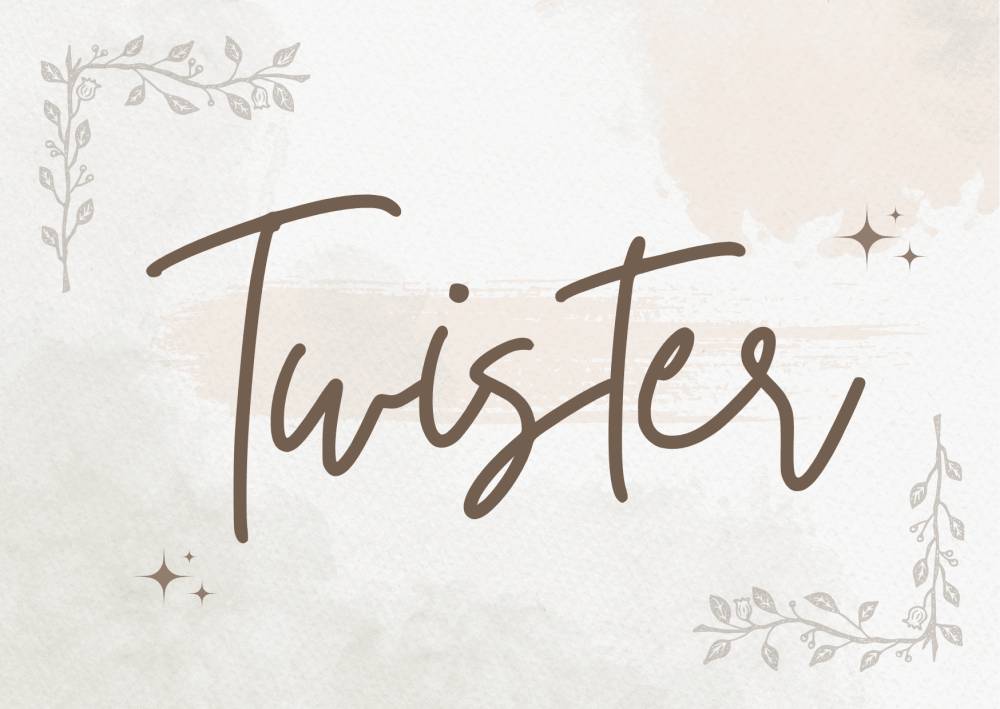
ilustrasi font Canva (dok. pribadi) 2. Angella White, font script dengan goresan halus dan lembut yang pas menambah sentuhan elegan branding produk kecantikan
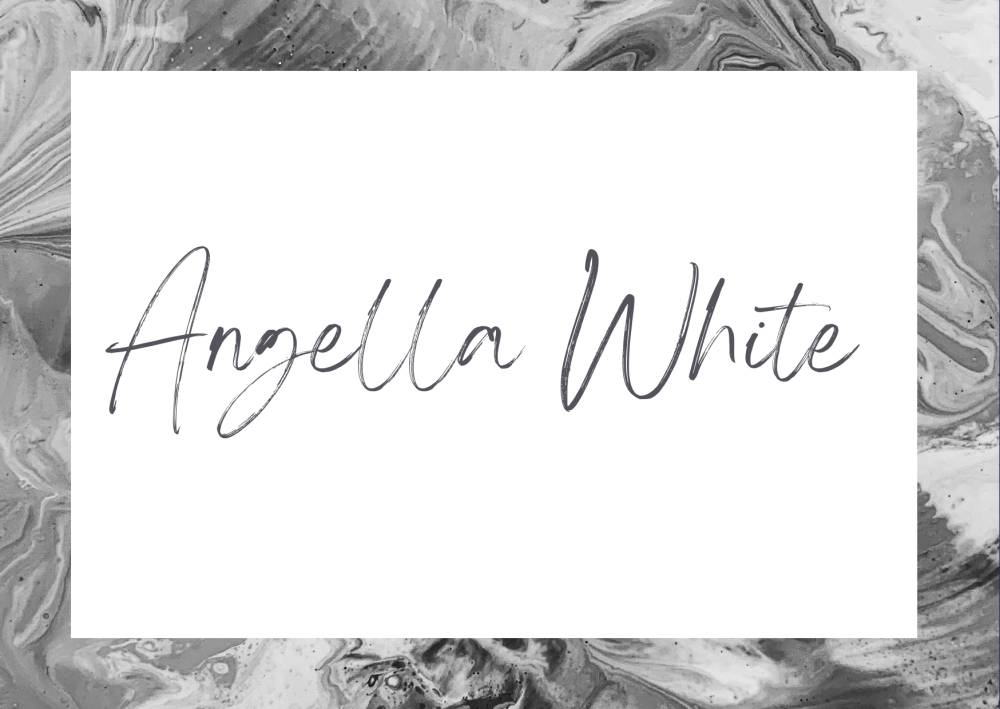
ilustrasi font Canva (dok. pribadi) 3. Virtual, font script yang terkesan clean, cocok digunakan buat desain produk cewek dengan tema minimalis
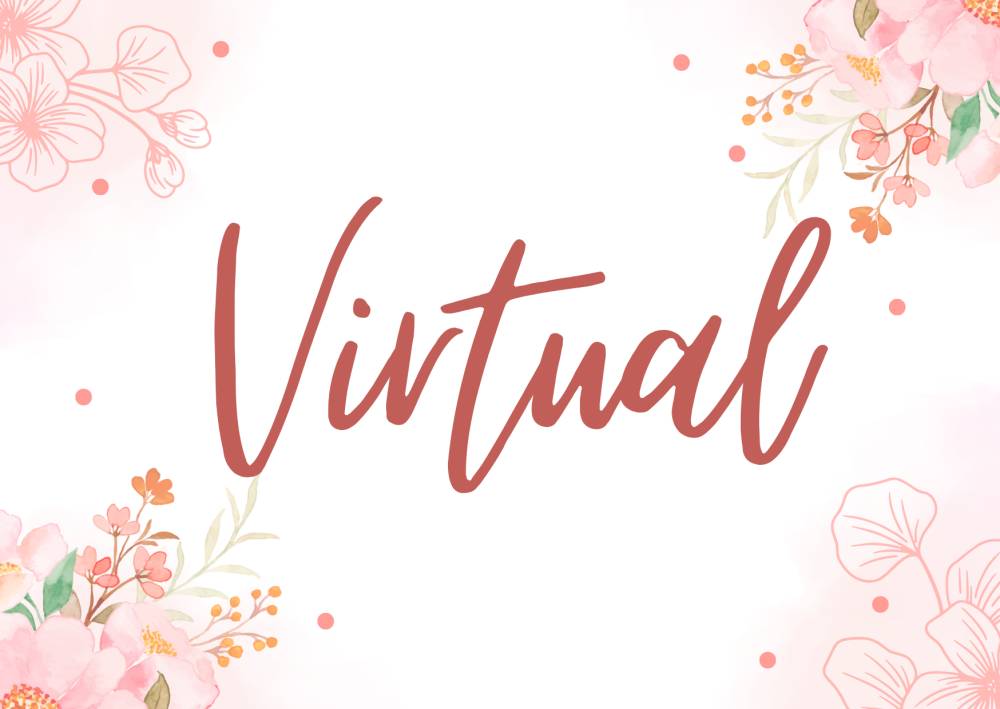
ilustrasi font Canva (dok. pribadi) 4. Playlist Script, font handwritten sejuta umat yang sering digunakan pada undangan pernikahan dan kartu ucapan
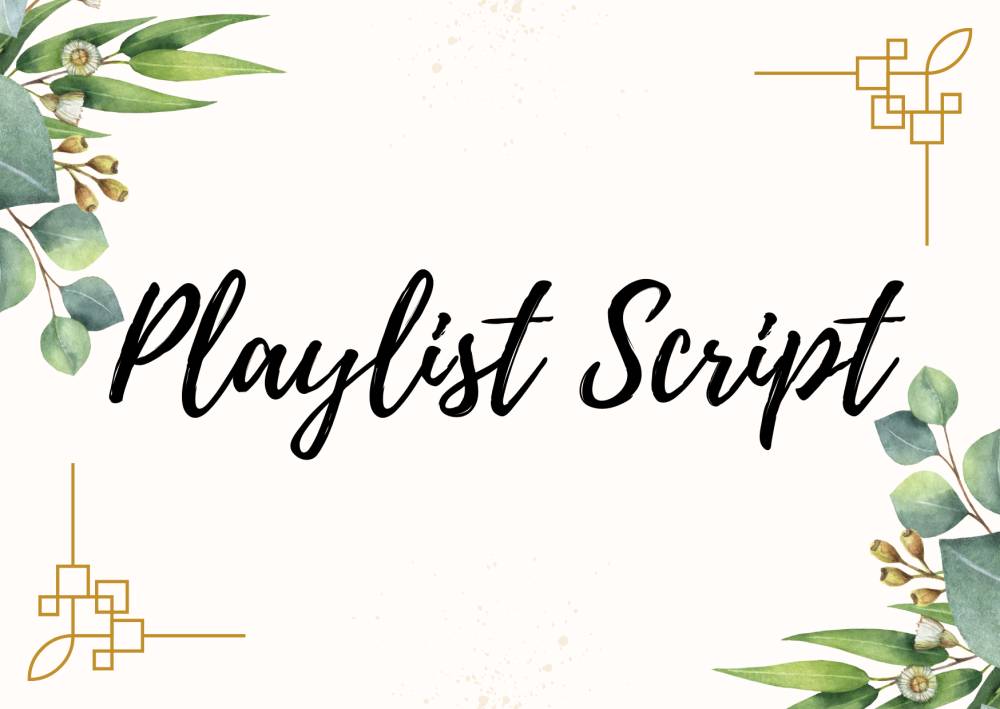
ilustrasi font Canva (dok. pribadi) 5. Brittany memiliki goresan lembut dan detail halus yang cocok dalam desain produk fashion menonjolkan sisi romantis nan anggun
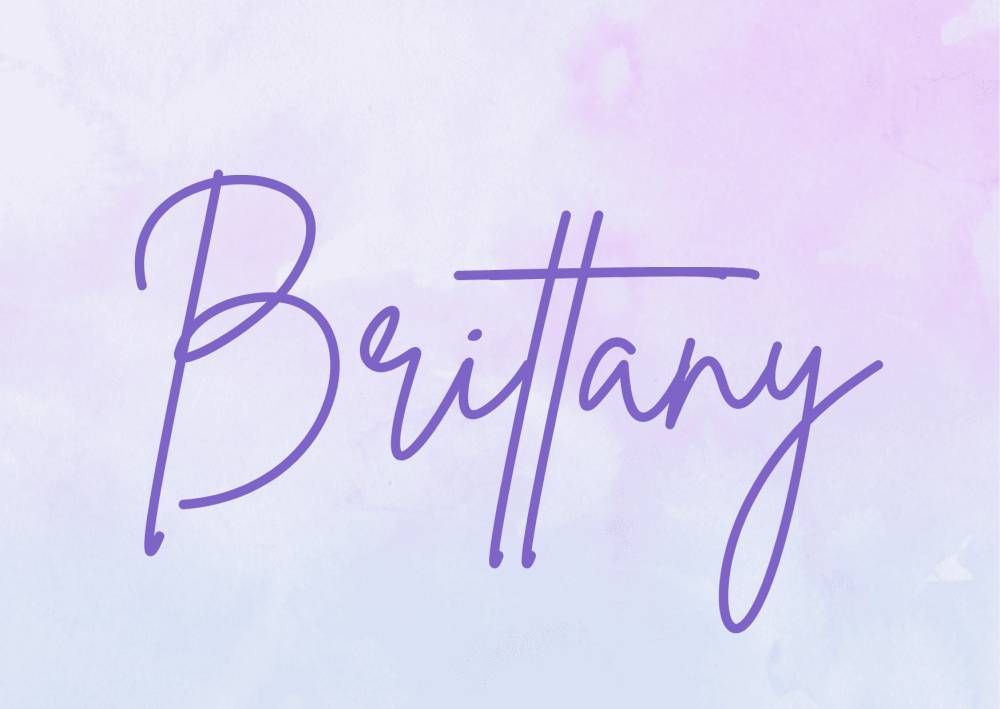
ilustrasi font Canva (dok. pribadi) 6. Aprila punya garis lengkungan khas dan girly abis, pas banget buat branding produk-produk cewek dengan detail warna-warni
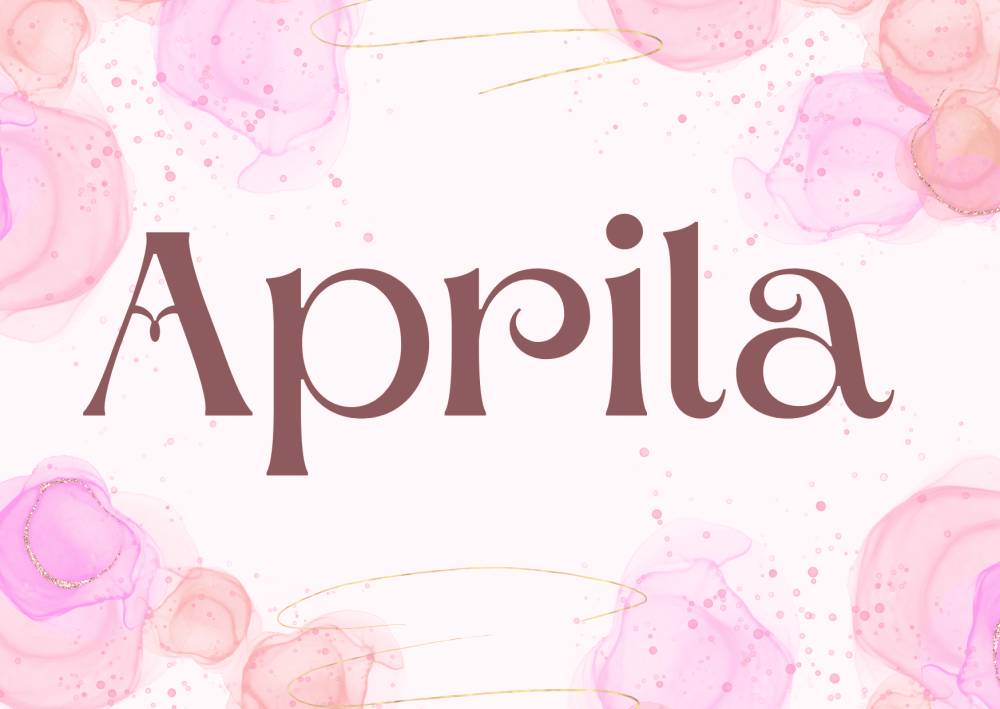
ilustrasi font Canva (dok. pribadi) 7. Angelina memberikan sentuhan artistik dan kesan anggun pada desain produk kecantikan dan fashion cewek
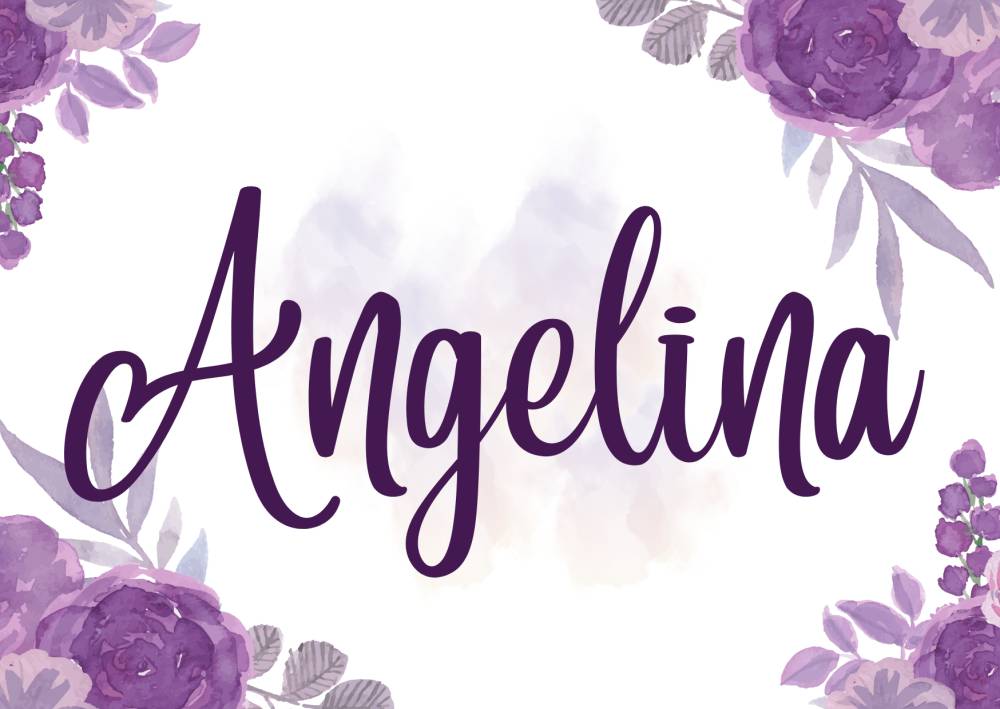
ilustrasi font Canva (dok. pribadi) 8. Euphoria Script punya kesan goresan dinamis dan bebas, cocok buat undangan pernikahan atau poster yang menekankan keceriaan
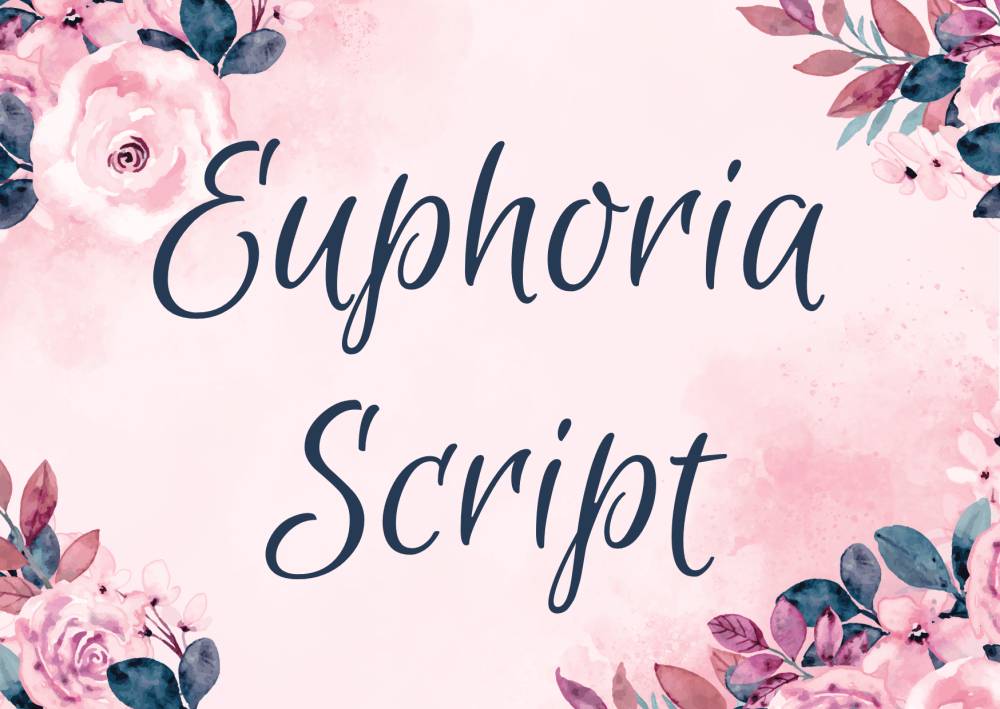
ilustrasi font Canva (dok. pribadi) Berbagai pilihan font feminin di atas bikin kamu gak perlu bingung lagi saat bikin desain yang bernuansa anggun dan girly. Tiap font ini memiliki ciri khas uniknya tersendiri yang menghasilkan kesan berbeda-beda saat diterapkan dalam desainmu. Pilih salah satu font di atas dan jangan lupa sesuaikan dengan fungsi desainmu agar pesan yang ingin disampaikan bisa tepat sasaran. Selamat berkreasi dan semoga desainmu selalu menginspirasi!